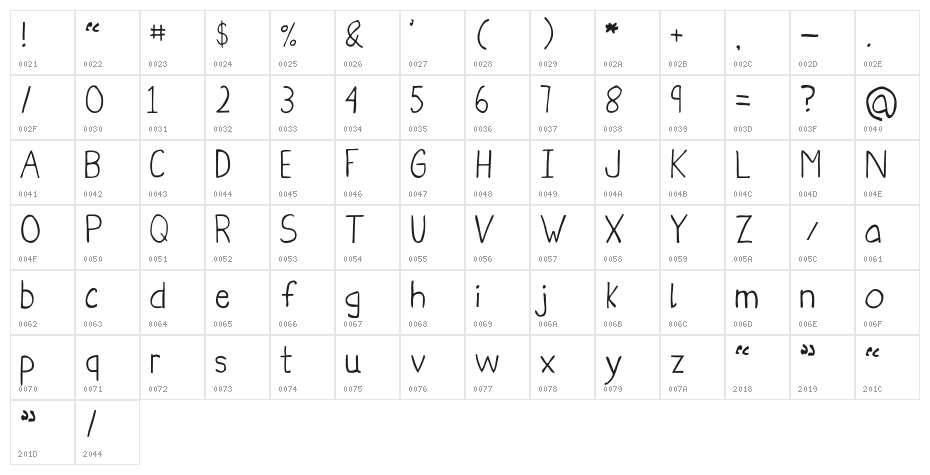
Obelisque Font
| Gesamtstil | Casual, Playful |
| Anwendungsfall | Headlines, Informal text, Creative projects |
| Vorgeschlagene Projekte | Ideal for greeting cards, children's books, personal blogs, and creative branding. |